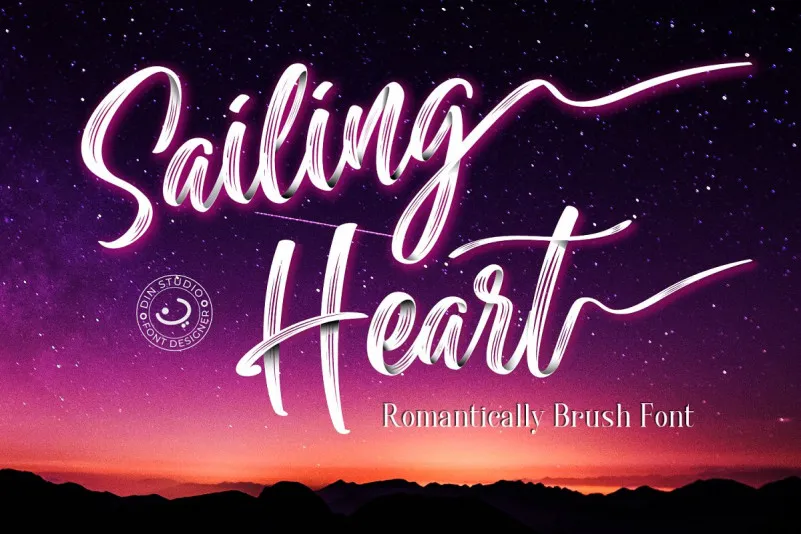
Sailing Heart Brush Font – Fonte Grátis
Sailing Heart Brush Font
Esta é uma fonte de script escrita a mão que inclui traços secos feitos com a forma do pincel e estilo de assinatura. Seu próximo destino está logo à sua frente? Comece sua jornada! Din Studio apresenta o mais recente produto, Sailing Heart Script ! Este é um belo tipo de script, criado usando naturalmente uma ponta de pincel. A textura desta fonte irá fazer seu design ainda mais bonito e poderoso. Esta fonte é adequada para qualquer projeto gráfico como marca, citações, convites para casamentos, projetos de letras e muito mais. A 24Design é o designer deste belo tipo de script, Sailing Heart Brush Font. Este tipo foi criado e compartilhado por Din Studio. A fonte Sailing Heart Brush Font possui uma textura natural do pincel que torna os designs mais atraentes e potentes. É perfeita para um vasto número de aplicações gráficas, desde criação de marca até convites de casamento, lembrancinhas personalizadas ou qualquer outro projeto de design em que seja necessário uma fonte de script.